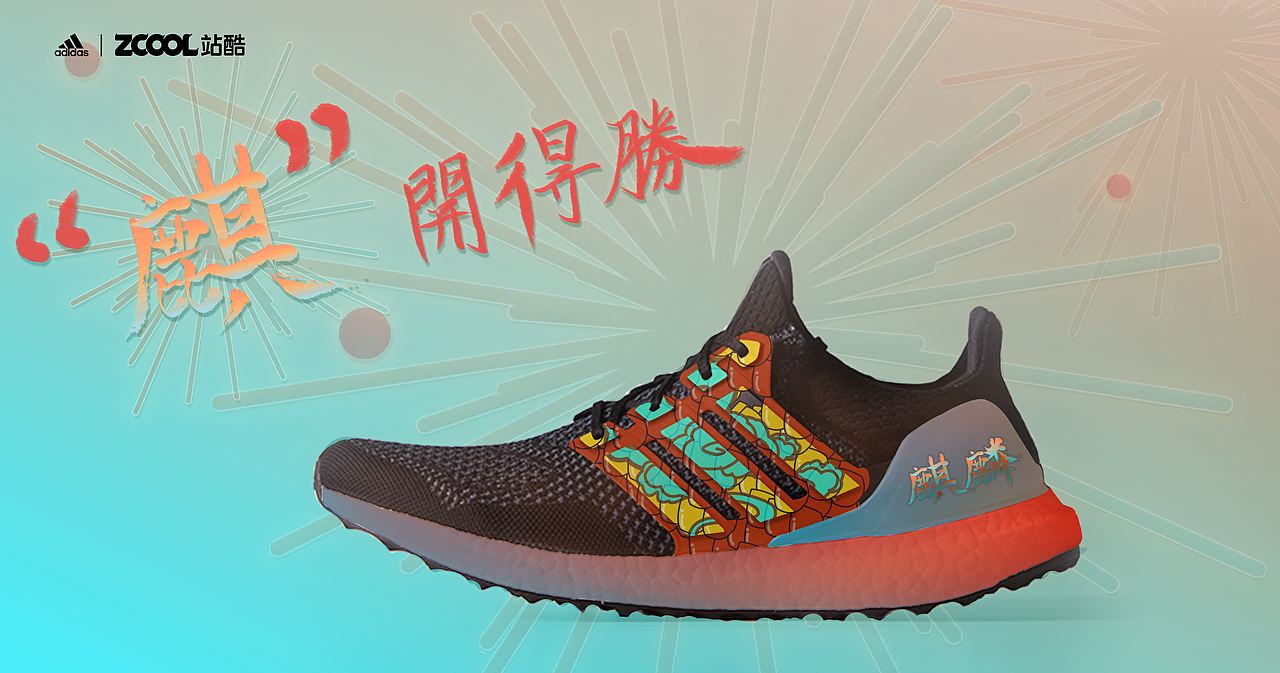
“麒”开得胜
麒麟:首似龙,形如马,状比鹿,尾若牛尾,背上有五彩毛纹,腹部有黄色毛,口能吐火,声音如雷。
麒麟乃中国古代神话传说中用以象征祥瑞的神兽,它的出现往往表示一种幸福。因此,古时人们希望麒麟总是伴随着自己,带来幸运和光明,辟除不祥。麒麟在《易冒》一书也将将其与青龙等四灵相提并论。
在中华民族传统的艺术宝库里,麒麟是我国历代人们喜闻乐见的装饰形象。这个瑰丽多姿、仪态万方的神灵瑞兽,不但集中了自然界各种动物美的大成,而且表现了超出自然本色的理想化的形式美,给人以吉祥的祝福和美的享受。
麒麟,不仅是祥瑞的象征,麒麟文化还反映出中华民族的大融合,是中华民族团结统一的象征。并且从春秋时代至今已经有二千五百多年,中国民间长久寄寓传颂的麒麟经雕刻,体现形态庄重,威而不猛,泰而不骄,贵而不俗,灵而不钝,蕴含着自强不息、厚德载福,向往盛世、平和可亲的精神,体现大中华风范。
麒麟在古时也用来比喻才能杰出、德才兼备的人。
作品中以“麒麟”为主体,添加一些龙鳞、祥云作为点缀;同时,“麒”谐音“旗”,象征旗开得胜,好运加身。